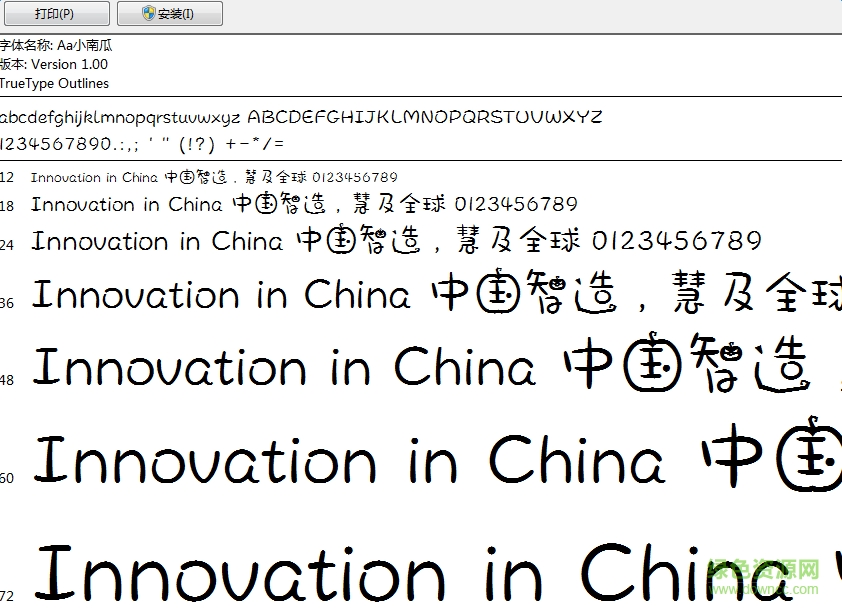
aaxiaonangua字體是一款形似小南瓜的中文可愛字體,外形圓滾滾,活潑可愛,像小孩子的手寫字體一樣,充滿天真童趣色彩,喜歡的小伙伴快來下載吧!
可愛字體生動(dòng)活潑,有鮮明的節(jié)奏韻律感,色彩豐富明快,給人以生機(jī)盎然的感受。這種個(gè)性的字體適用于兒童用品、運(yùn)動(dòng)休閑、時(shí)尚產(chǎn)品等主題!